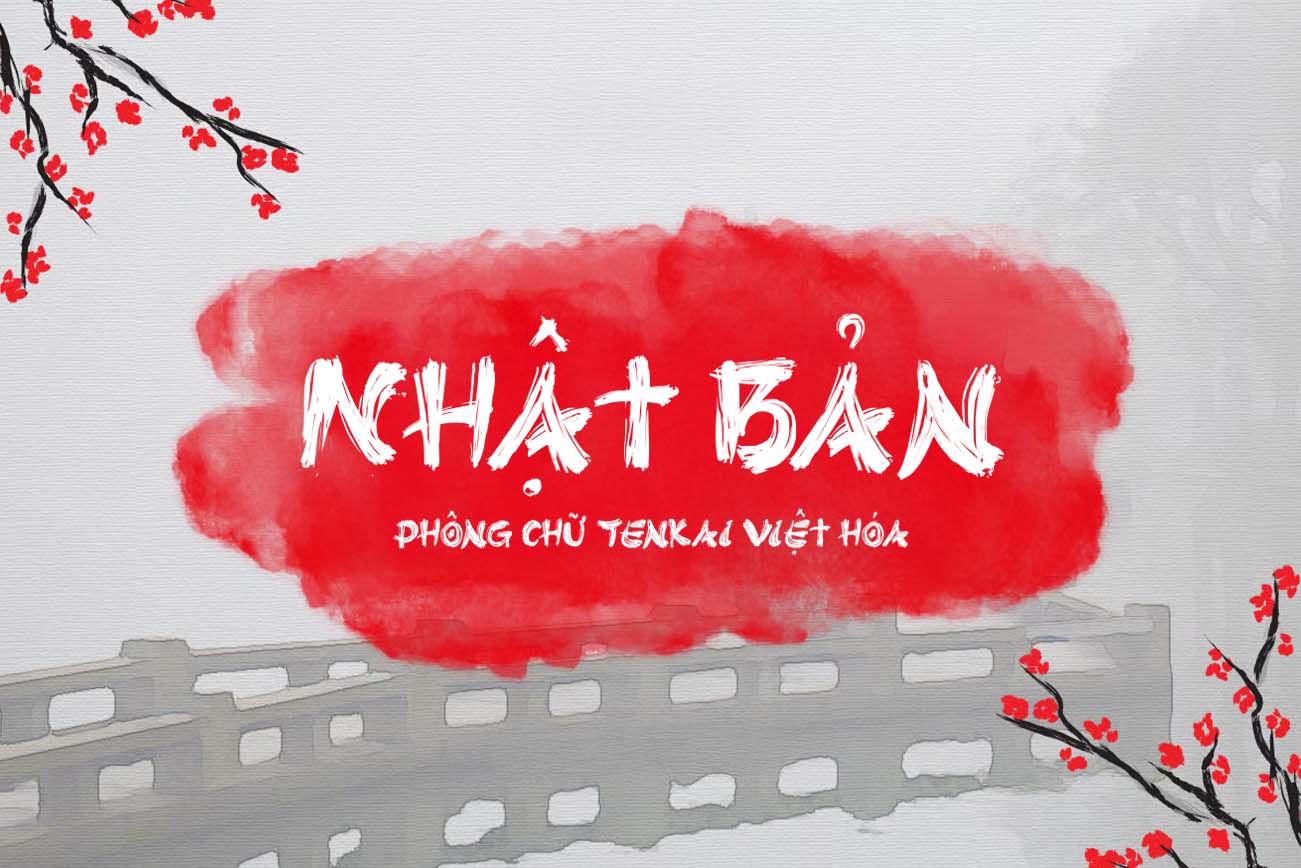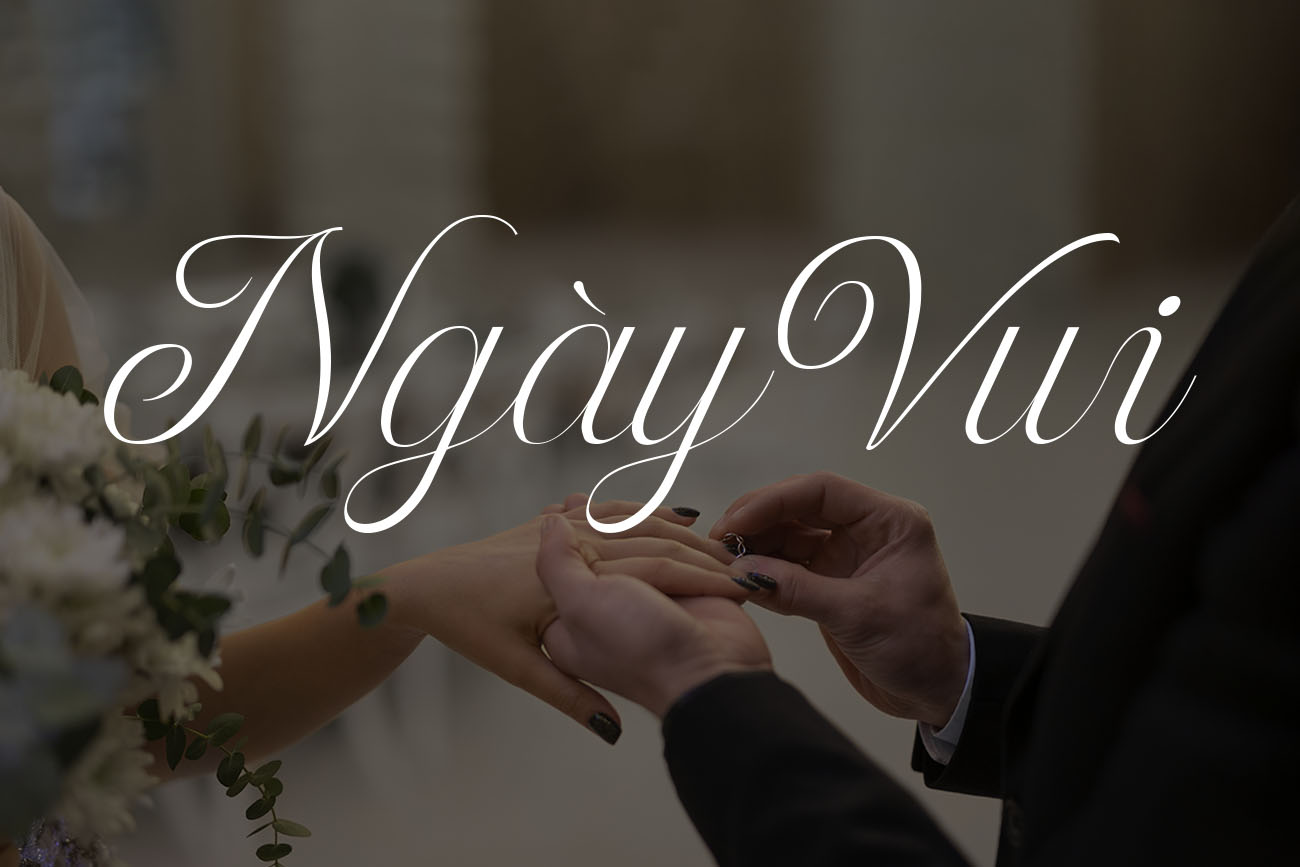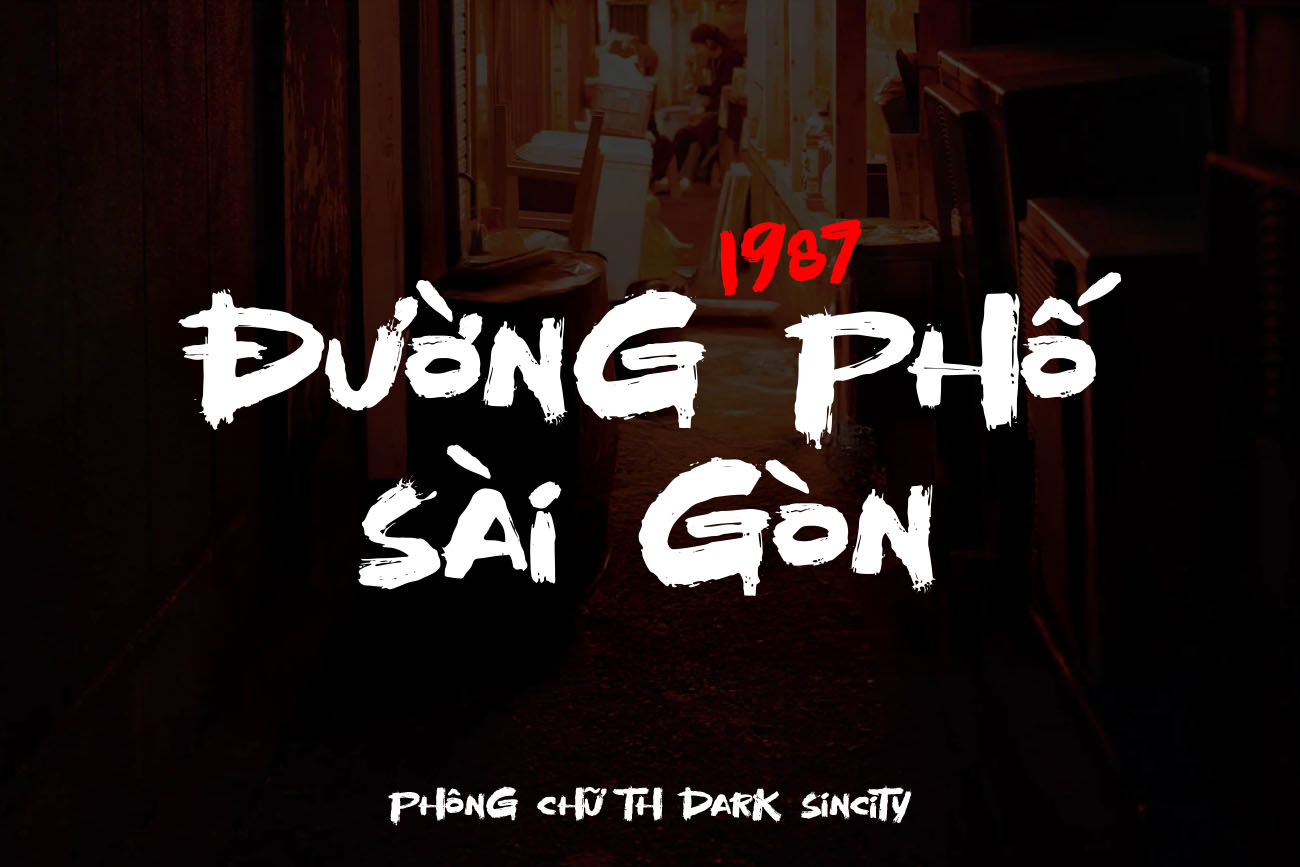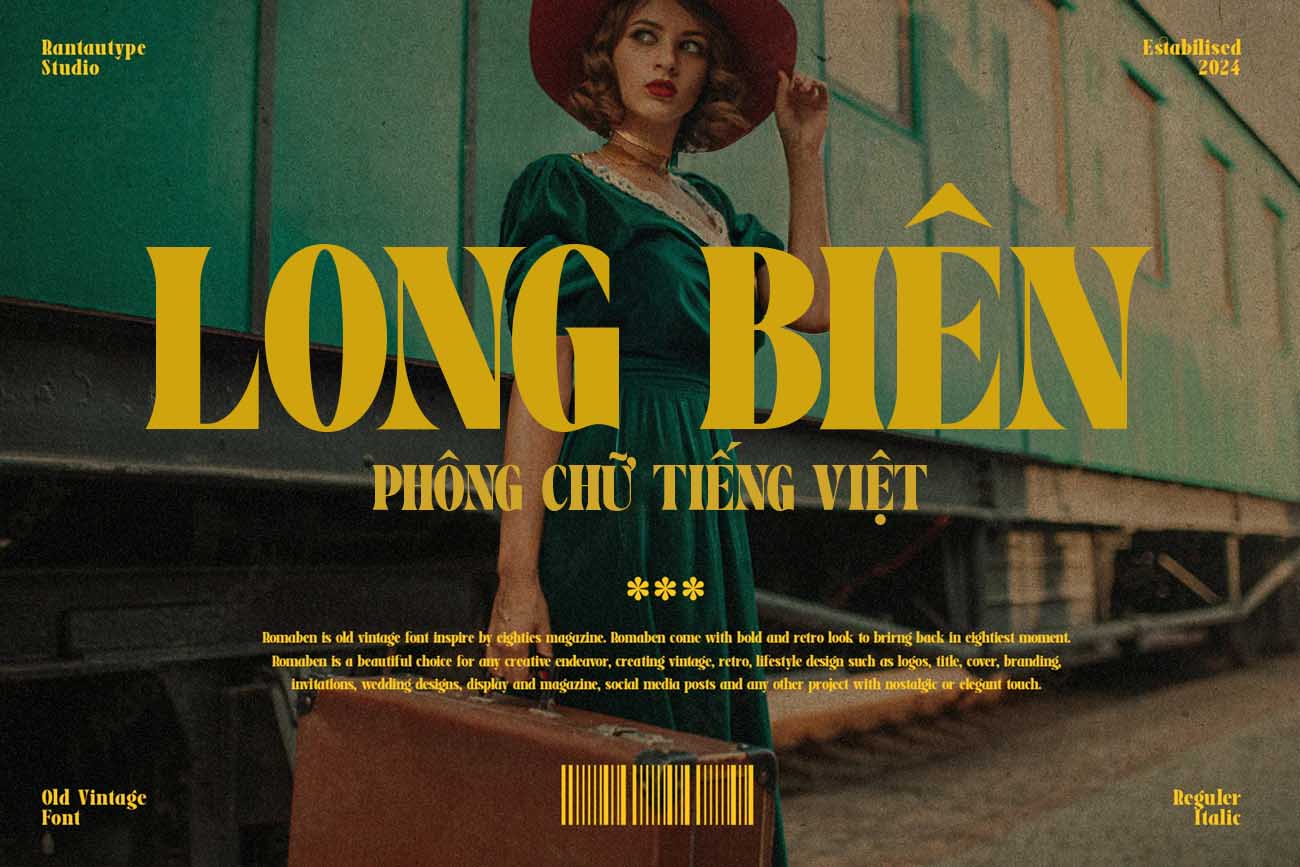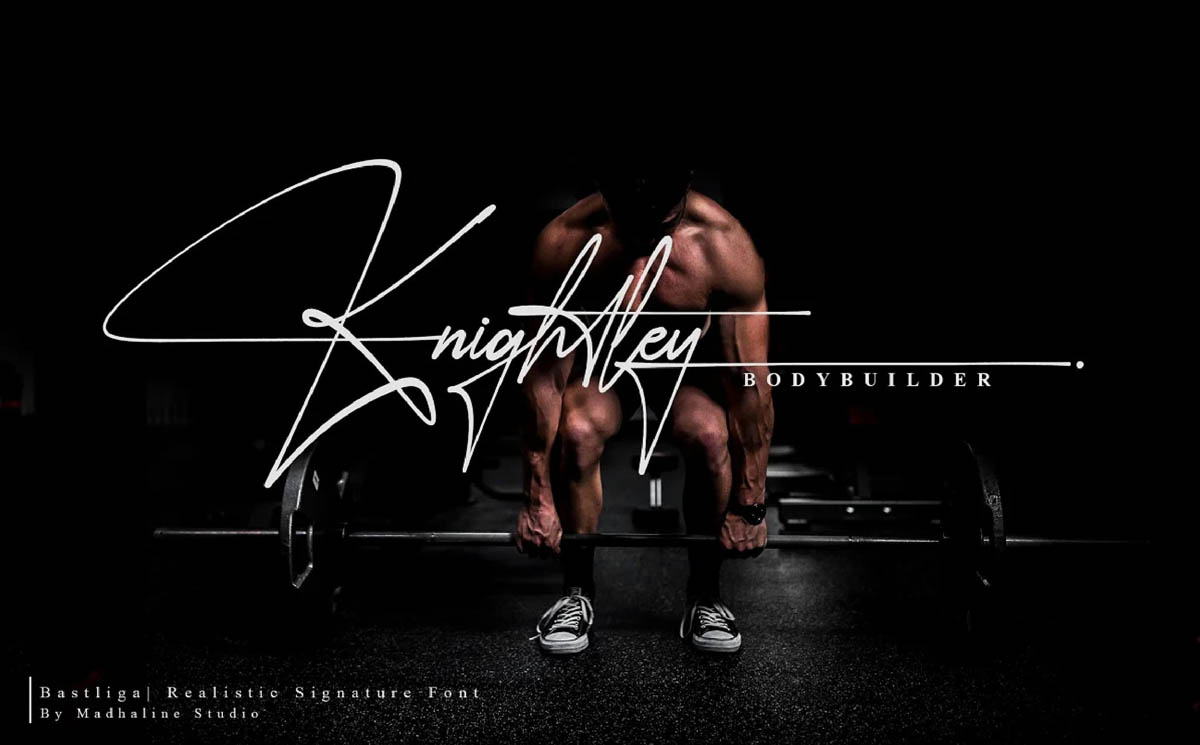
Top 15 font chữ cho workshop, lớp học nghệ thuật và sự kiện cộng đồng
Gợi ý 15 font TH Việt hóa phù hợp cho workshop, lớp học nghệ thuật, creative class, poster sự kiện cộng đồng và social post sáng tạo.
Một poster workshop tốt cần tạo cảm giác “muốn tham gia” ngay từ cái nhìn đầu tiên. Khác với banner sale hay catalogue, thiết kế cho lớp học nghệ thuật và sự kiện cộng đồng thường cần ấm hơn, gần hơn và có dấu vết con người hơn. Vì vậy font chữ không chỉ để đọc thông tin, mà còn giúp người xem hình dung không khí của buổi học: vui, chậm rãi, sáng tạo, thủ công, cá tính hay chuyên nghiệp.
Bài viết này gợi ý 15 font TH Việt hóa phù hợp cho poster workshop, lớp học nghệ thuật, creative class, buổi nói chuyện cộng đồng, lớp thủ công, lớp vẽ, lớp làm bánh, lớp cắm hoa và các sự kiện sáng tạo nhỏ. Danh sách ưu tiên các font viết tay, script, brush, sans display và một số font hoài cổ dễ dùng, để anh có nhiều lựa chọn hơn ngoài nhóm font doanh nghiệp hoặc font khai trương đã dùng gần đây.
Cách chọn font workshop Việt hóa cho poster và social post
Khi chọn font workshop, anh nên nhìn vào ba yếu tố: chủ đề lớp học, độ tuổi người tham gia và kênh truyền thông. Workshop trẻ em hoặc làm bánh có thể dùng font tròn vui. Workshop vẽ, viết chữ, cắm hoa hợp với font script mềm. Creative talk, portfolio review hoặc lớp thiết kế nên chọn font display có cá tính nhưng không quá khó đọc. Với sự kiện cộng đồng, font cần thân thiện và rõ thông tin vì người xem thường đọc nhanh trên điện thoại.
Một bố cục dễ dùng là: font nổi bật cho tên workshop, font phụ dễ đọc cho thời gian/địa điểm/giá vé, và một font trung tính cho mô tả ngắn. Đừng dùng quá nhiều font trang trí trong cùng poster, vì workshop cần cảm giác mời gọi, không phải cảm giác rối mắt.
Top 15 font chữ cho workshop, lớp học nghệ thuật và sự kiện cộng đồng
1. TH Viettay 7 - poster workshop vẽ tay, lớp thủ công, buổi journaling hoặc lớp sáng tạo nhỏ
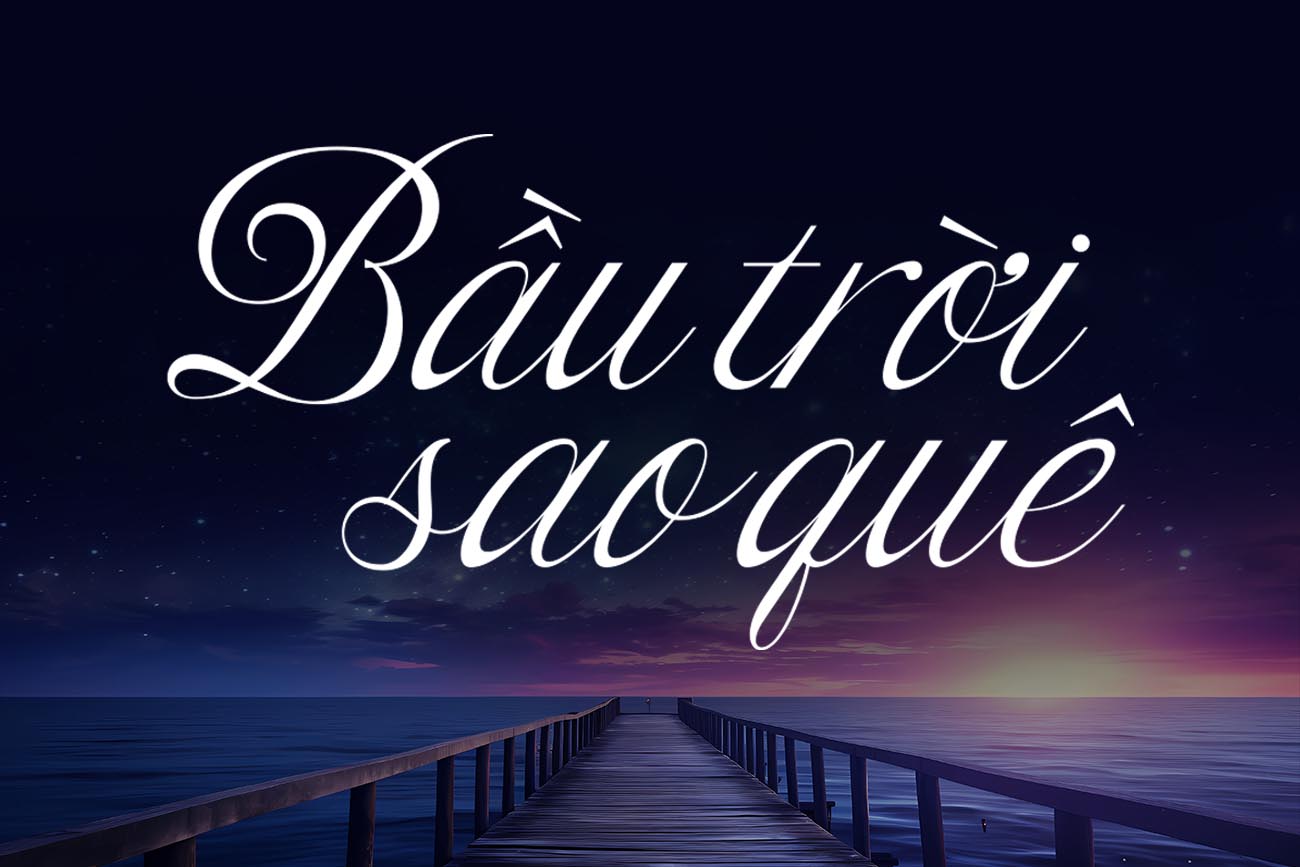
Tải font TH Viettay 7 nếu anh đang làm poster workshop vẽ tay, lớp thủ công, buổi journaling hoặc lớp sáng tạo nhỏ. Điểm mạnh của TH Viettay 7 là nét mảnh uốn lượn tạo cảm giác người thật viết, rất hợp với tinh thần thân thiện của lớp học nghệ thuật. Khi đặt trên poster workshop, font này nên dùng cho cụm chữ chính như “Workshop cuối tuần”, “Lớp vẽ màu nước”, “Creative Class”, “Art & Craft” hoặc tên riêng của buổi học.
Để thiết kế dễ đọc hơn, anh nên để TH Viettay 7 làm phần nhấn, còn lịch học, địa điểm, học phí, form đăng ký và lưu ý dành cho học viên nên dùng một font sans-serif đơn giản. Cách này giữ được tinh thần sáng tạo mà vẫn không làm mất thông tin quan trọng.
2. TH Mrattoos Regular - poster workshop lettering, calligraphy, vẽ tranh, làm sổ tay hoặc sự kiện chia sẻ kỹ năng
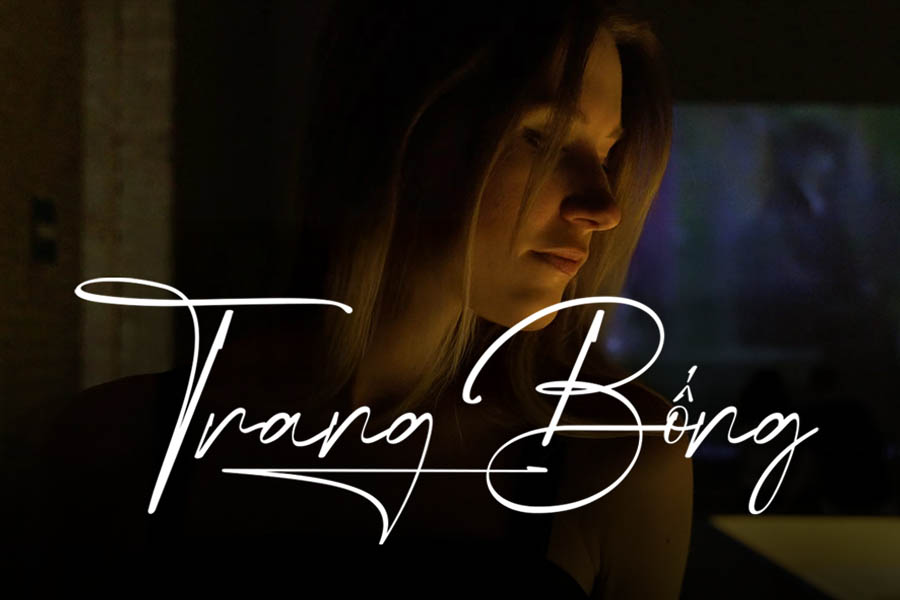
Tải font TH Mrattoos Regular nếu anh đang làm poster workshop lettering, calligraphy, vẽ tranh, làm sổ tay hoặc sự kiện chia sẻ kỹ năng. Điểm mạnh của TH Mrattoos Regular là chất chữ ký mềm và bay giúp tiêu đề có cảm xúc, phù hợp khi lớp học muốn tạo cảm giác cá nhân. Khi đặt trên poster workshop, font này nên dùng cho cụm chữ chính như “Workshop cuối tuần”, “Lớp vẽ màu nước”, “Creative Class”, “Art & Craft” hoặc tên riêng của buổi học.
Để thiết kế dễ đọc hơn, anh nên để TH Mrattoos Regular làm phần nhấn, còn lịch học, địa điểm, học phí, form đăng ký và lưu ý dành cho học viên nên dùng một font sans-serif đơn giản. Cách này giữ được tinh thần sáng tạo mà vẫn không làm mất thông tin quan trọng.
3. TH Bengoda - poster lớp vẽ màu nước, workshop cắm hoa, lớp làm nến thơm hoặc sự kiện dành cho nữ
Tải font TH Bengoda nếu anh đang làm poster lớp vẽ màu nước, workshop cắm hoa, lớp làm nến thơm hoặc sự kiện dành cho nữ. Điểm mạnh của TH Bengoda là đường chữ mềm mại, thanh thoát, hợp làm điểm nhấn cho tên workshop hoặc tagline. Khi đặt trên poster workshop, font này nên dùng cho cụm chữ chính như “Workshop cuối tuần”, “Lớp vẽ màu nước”, “Creative Class”, “Art & Craft” hoặc tên riêng của buổi học.
Để thiết kế dễ đọc hơn, anh nên để TH Bengoda làm phần nhấn, còn lịch học, địa điểm, học phí, form đăng ký và lưu ý dành cho học viên nên dùng một font sans-serif đơn giản. Cách này giữ được tinh thần sáng tạo mà vẫn không làm mất thông tin quan trọng.
4. TH Jalliya - poster lớp nghệ thuật nhẹ nhàng, buổi chia sẻ sáng tạo, thiệp mời workshop và moodboard social
Tải font TH Jalliya nếu anh đang làm poster lớp nghệ thuật nhẹ nhàng, buổi chia sẻ sáng tạo, thiệp mời workshop và moodboard social. Điểm mạnh của TH Jalliya là có nhiều kiểu chữ ký nên linh hoạt khi cần tạo hierarchy giữa headline và cụm nhấn. Khi đặt trên poster workshop, font này nên dùng cho cụm chữ chính như “Workshop cuối tuần”, “Lớp vẽ màu nước”, “Creative Class”, “Art & Craft” hoặc tên riêng của buổi học.
Để thiết kế dễ đọc hơn, anh nên để TH Jalliya làm phần nhấn, còn lịch học, địa điểm, học phí, form đăng ký và lưu ý dành cho học viên nên dùng một font sans-serif đơn giản. Cách này giữ được tinh thần sáng tạo mà vẫn không làm mất thông tin quan trọng.
Font workshop Việt hóa nên tạo cảm giác sáng tạo, thân thiện và đúng không khí lớp học. Một lớp nghệ thuật nhỏ không cần font quá “gào”, nhưng cũng không nên dùng font văn phòng quá khô. 15 font TH trong bài này giúp anh có đủ lựa chọn từ mềm mại, viết tay, vui tươi đến hoài cổ và chuyên nghiệp.
Khi chọn font cuối cùng, hãy đặt thử vào đúng nội dung poster thật: tên workshop, lịch học, địa điểm, học phí và lời kêu gọi đăng ký. Font tốt là font khiến người xem hiểu nhanh lớp học nói về điều gì, cảm thấy buổi học có không khí riêng và muốn bấm đăng ký ngay.